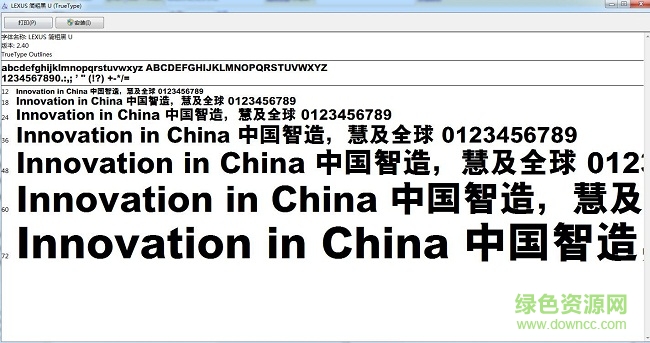
lexus 簡(jiǎn)粗黑 u xbold
lexus-heis-xbold-u字體又叫雷克薩斯簡(jiǎn)粗黑字體,是一款適用性很強(qiáng)的黑體字體,設(shè)計(jì)感強(qiáng)烈,易用耐看,用在海報(bào)上再合適不過了,喜歡的朋友快來綠色資源網(wǎng)下載吧!
黑體字體介紹
1.黑體屬于無襯線字體類,字體方正,筆畫醒目粗狀,識(shí)別度比宋體更高些,比較直接干練,是機(jī)器印刷的歷史產(chǎn)物;
2.最大特征就是可塑性強(qiáng)。不同字重的黑體表現(xiàn)出來的氣質(zhì)也不一樣;
3.粗黑體大多商業(yè)用的標(biāo)題使用,纖細(xì)黑體則可以表現(xiàn)在女性用品方面。
lexus heis xbold u字體